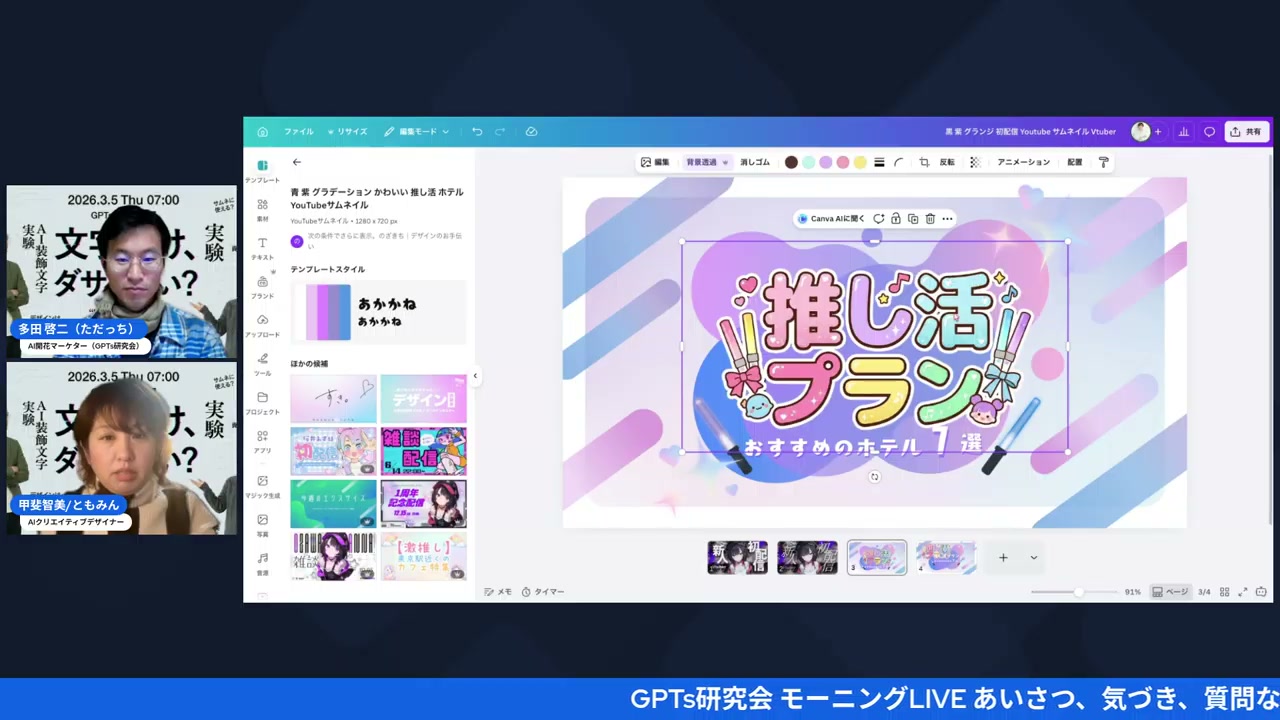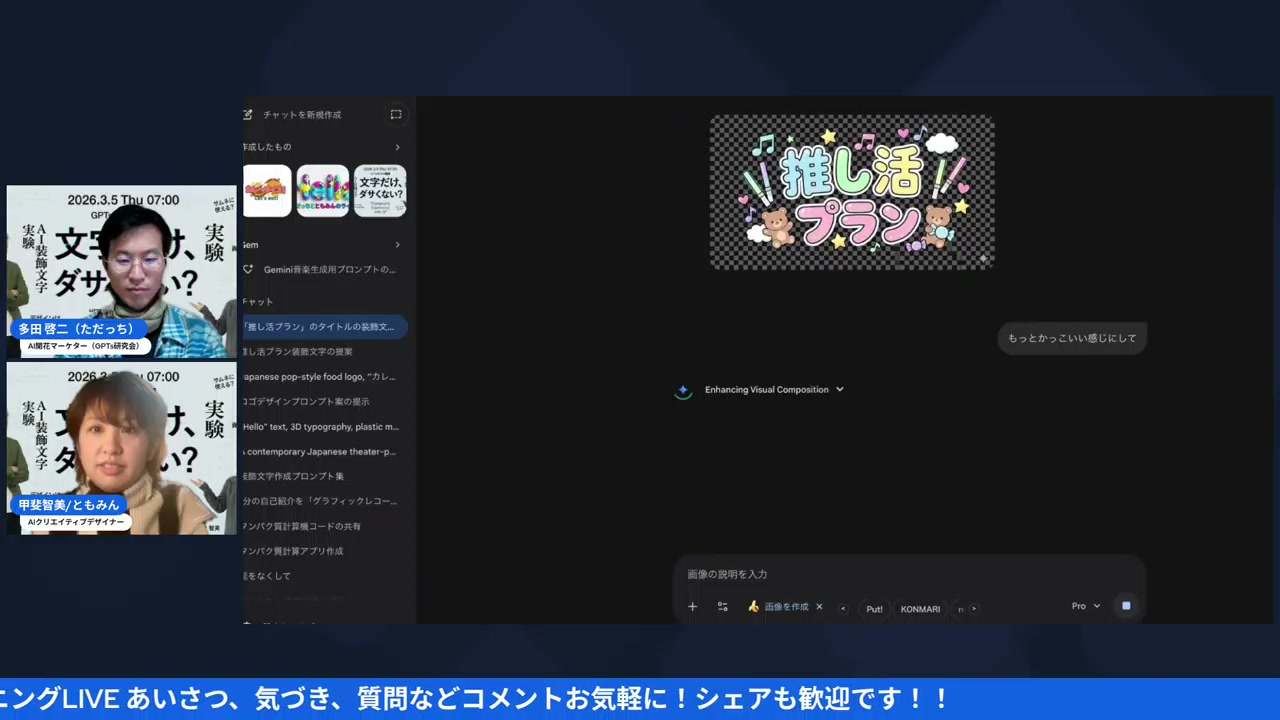
文字ひとつで印象が変わる、Canvaプロモード装飾文字実験
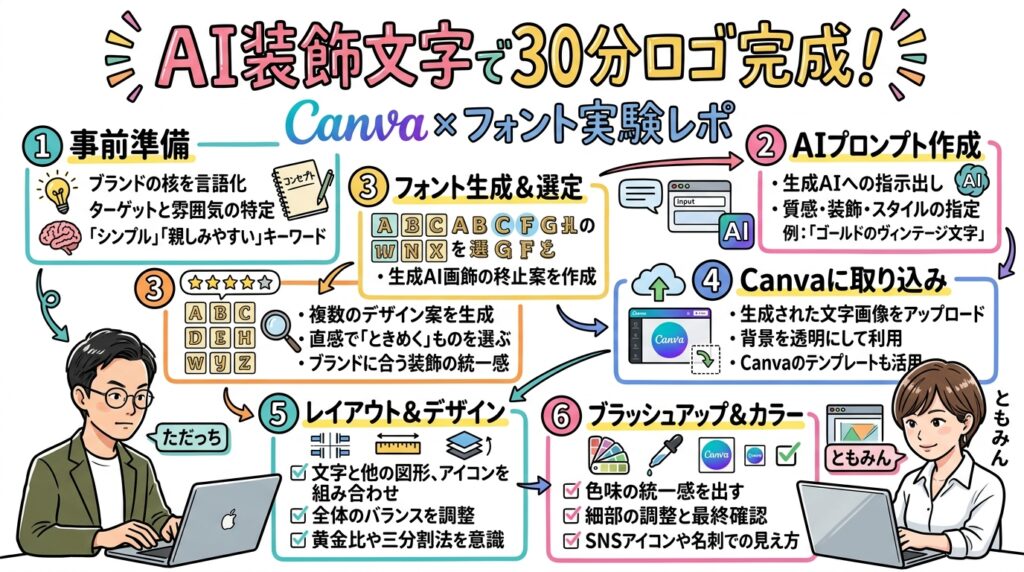
家事と子育てのスキマで経営する3方よしAI共創コンサルタントの田中啓之、ひろくん(@passion_tanaka)です。今回はともみん(甲斐智美)が語った、Canvaプロモードで文字を装飾するLIVEを紹介するね。木曜あさのGPTs研究会、進行役はただっち(多田啓二)。この日、私は登壇していなくて、画面の外から二人のやり取りをそのまま見ていた立場で、今日はお届けします。
いやー、この回は最初から最後まで「文字」の話しかしてないんだけど、それがめちゃくちゃ濃かった。テーマは「AI装飾実験」。ゴシックとミンチョ、たった2種類のフォントの見分け方から始まって、Canvaプロモードで装飾文字を生成し、背景を透過してレイヤーに重ねる。地味な操作の積み重ねが、最後には「同じ推し活プランのタイトルなのに、こんなに違うの?」というビフォーアフターにつながっていった。その一部始終を、今日は紹介するね。
文字ひとつで印象が変わる——AI装飾実験のはじまり
木曜あさのLIVEは、ただっちの挨拶から始まった。この日のテーマは「AI装飾実験」。文字ひとつで全然イメージが変わるし、そこにAIの力を借りられる時代になった、という導入だった。
ただっち(0:37〜)
「この文字にこのなんかえっと思いを込めるっていうのはすごいなというふうにいつも思っておりまして、今日はそんな文字装飾もAIの力も借りられるというところですね、実験してお届けしたいなと思っています」
文字に思いを込める、という言葉、私はすごく共感しました。
自己紹介を挟んで、ただっちは自身とともみんの出会いについても触れていた。友人と出会ったことで表現の幅が広がった、という話。
ただっち(0:37〜)
「友人とも出会ったことで表現の幅がすごく僕も広かったなと思っています。デザイン一つで思いを伝えられる可能性というのは広がっているんじゃないかなと思いますので、今日トモミンの文字装飾も楽しみにしておりました」
デザインひとつで思いを伝えられる、という視点、私はいいなと思いました。
正直、この時点ではまだ「文字の実験」がどれくらい面白いのか分からなかった。半信半疑。……でも、ともみんの一言で、それがちゃんと本気の実験だってわかる。
ともみん(1:41〜)
「私も最近ちょっと文字をAIで別に作るようになりまして、これをやるだけで結構パターンが変わってきたりビジュアルが大きく変わるなと思ったので、ちょっと今日はこの題にしたいなと思っております」
文字だけでビジュアルが大きく変わる、と私は感じました。この一言が、今日一日のテーマを決めていたんだなあと思う。
ただっちとともみんは、それぞれ「AI開花マーケター」「AIクリエイティブデザイナー」として自己紹介していて、二人とも普段からAIを使ったデザインの現場に立っている人たちだった。だからこそ、今日の実験は単なる思いつきじゃなくて、日々の仕事の延長線上にある本気の検証だったんだと思う。木曜のGPTs研究会は、こういう「実際にやってみせる」LIVEが多いんだけど、この回はその中でも特に手を動かす時間が長かった印象。二人のテンションも最初から高くて、コメント欄にも「おはよう」が続々と流れていた。
私、この冒頭のやり取りを見ながら、二人の関係性がすごくいいなと思っていた。ただっちがともみんを「今日トモミンの文字装飾も楽しみにしておりました」と紹介し、ともみんもそれに応えるように「私も最近ちょっと文字をAIで別に作るようになりまして」と自分の実感を重ねていく。この掛け合いのテンポの良さが、そのまま今日30分の中身の濃さにつながっていったんだと思う。文字装飾という一見地味なテーマを、ここまで前のめりに語れるのは、二人がAIとデザインの現場に日々向き合っている証拠なんだろうなあ。
あ、そうだ。ひとつ言い忘れてた。この日のテーマ名、正式には「AI装飾実験」なんだよね。実験。この言葉がすごく大事で……二人とも「これが正解です」って上から教える感じじゃなくて、「一緒にやってみましょう」っていう温度だった。私、そこがいちばん好きなんですよ。画面のこっち側で見ていても、失敗も含めて全部さらけ出してくれるから、こっちも身構えずに済む。
ぶっちゃけ、文字の話って地味でしょ。フォントがどうとか配置がどうとか、聞く前は「まあ知っといて損はないかな」くらいのテンションだった。……でもね。ともみんの『これをやるだけで結構パターンが変わってきたりビジュアルが大きく変わる』っていう一言で、一気に前のめりになっちゃった。たった文字ひとつで、作るものの印象が根っこから変わる。そんな話を、朝いちばんの30分でここまで掘り下げるLIVEって、なかなかないんですよ。だから今日のこのレポも、ぜひ最後まで付き合ってほしいなあと思ってます。
文字はまず2種類——ゴシックとミンチョの話
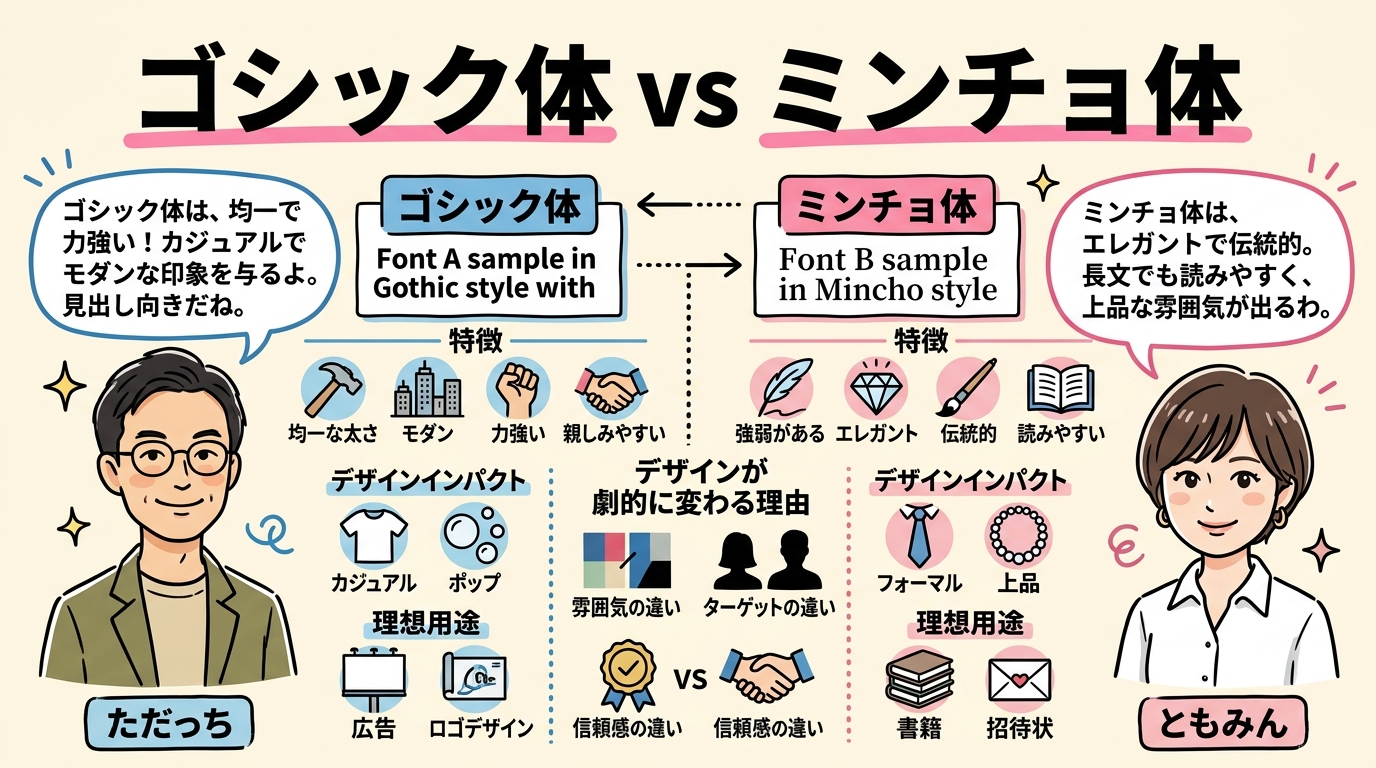
いくつかサンプルを見比べながら、ともみんが切り出したのは「文字は2種類だけ知っておけば十分」という話だった。デザイナーが見て「あ、この文字これだわ」ってわかるのも、結局この2種類の話に集約されるらしい。
ともみん(6:34〜)
「あれなんだよね。結構デザイナーの人がさ、こうやって見てて、あ、この文字これだわみたいなのって分かったりするんだけど。基本的に文字って2種類。2種類。日本語で言うと、」
でね、これが私には意外だったんですよね。フォントって選択肢が無限にあるように見えて、実は「尖ってるか、シュッとしてるか」の2軸に落とし込めるって話。シンプル。
この後、ともみんは「だいたいコシックかミンチョウの2種類」という表現でもう一度まとめ直していて、配置の話にもつながっていく。
ともみん(7:26〜)
「そうそうそうそう。だいたいコシックかミンチョウの2種類になっているので、これ多分でもねこういう感じだったらあとねよくあるのはこれ配置がねちょっといつもと違うとかいうときあると思うの」
フォントの種類だけじゃなく、配置までワンセットで印象が決まる——このことに私、この時点で気づかされました。
ただっちも「それね」と相槌を打ちながら聞いていて、二人の間ではもう当たり前の知識みたいだったけど、私にとっては新鮮な整理の仕方だった。ゴシックとミンチョ、この2択だけ覚えておけば、文字選びで迷う場面はぐっと減るんだろうなあ、と思いながら見ていた。派手なツールの機能紹介よりも、こういう地に足のついた話のほうが、実は一番使える知識だったりするんだよね。
面白いのは、この2種類の話が「機能の説明」じゃなくて「見た瞬間の印象の話」として語られていたところ。ゴシックは先っぽが尖っていて力強い印象、ミンチョはシュッとしていて上品な印象。デザインの専門用語を並べられるより、こっちのほうがずっと頭に残るなあと私は感じた。木曜LIVEでは毎回こういう、覚えやすい言い換えがぽんぽん出てくるのが特徴だなと、あらためて思う。
でね、私がこの「2種類だけ」って話を聞いて思ったのは……料理でいうと、包丁を全種類そろえる前に「切る」と「刻む」の2つを覚えるようなものだなあ、と。フォントも同じ。何百種類ある中から選ぶんじゃなくて、まず「ゴシックか、ミンチョか」。この2択にさえ落とせば、もう迷子にならない。入り口がこれくらい単純だと、はじめてでも手が動くんですよ。
しかもともみんは、フォントの種類だけじゃなくて『配置がちょっといつもと違うとかいうときあると思うの』って、置き方にまで話を広げてた。種類+配置。この2つがワンセットで印象を決めてるんだよね。……知ってしまえば当たり前。でも、言葉にしてもらえるまで、私はぼんやりとしか分かってなかった。ゴシックは力強い、ミンチョは上品——たったこれだけの物差しを手に入れるだけで、次に何か作るときの目線が変わる気がしたんですよ。
今回の題材である「推し活プラン」の文字も、結局はこの2種類のどちらに寄せるかで方向性が決まっていく。ゴシック寄りにすればしっかりした印象、ミンチョ寄りにすれば柔らかい印象。次のセクションで実際にともみんが手を動かしていく様子を見ると、この「2種類のどちらか」という判断がいかに最初の分かれ道になっているかがよくわかる。
文字の話って、つい難しく考えがちだけど、入り口はこれくらいシンプルでいいんだなと、私は今日の説明を聞いて肩の力が抜けた気がした。
「推し活プラン」の文字をCanvaプロモードでロゴにしてみる
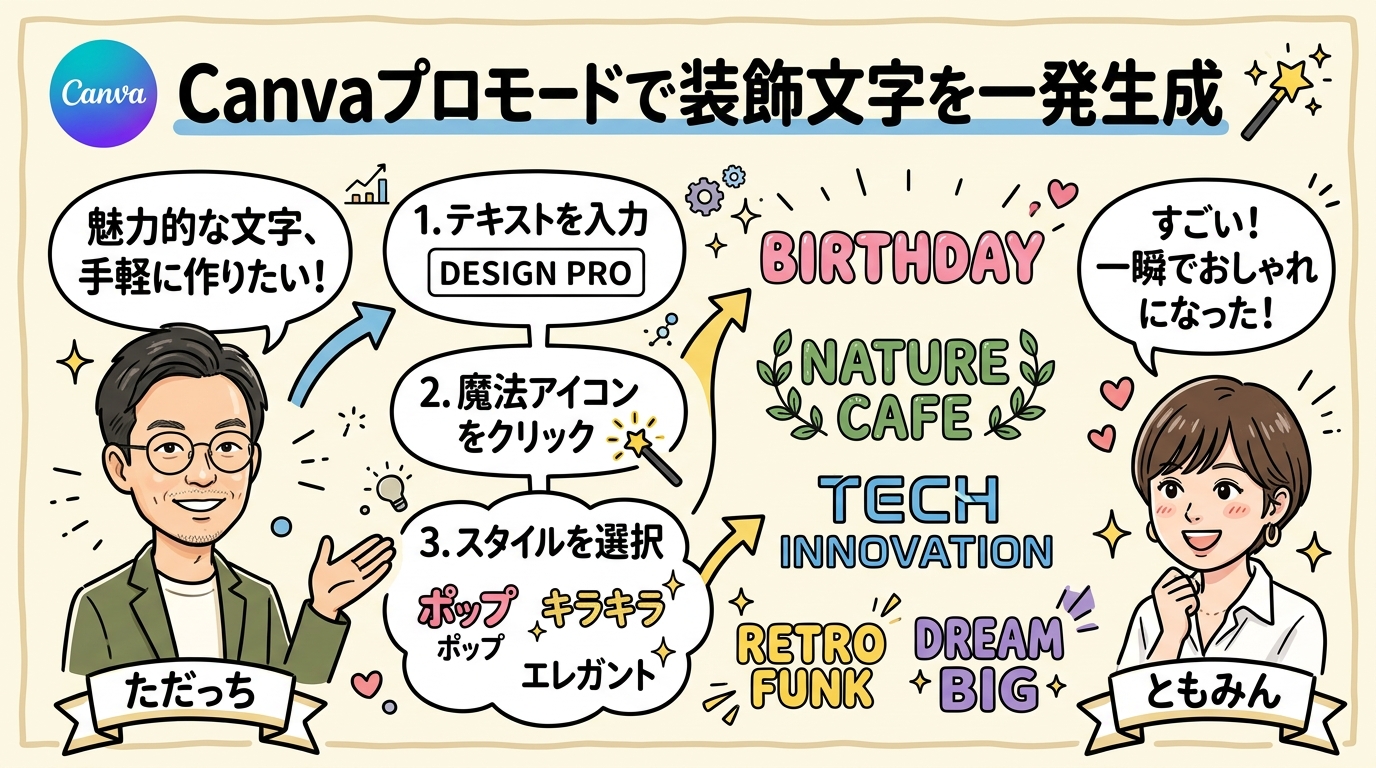
いよいよ実演パート。お題は「推し活プラン」というタイトル文字。画面上では「押し勝つプラン」って変換されたり、コメント欄で突っ込まれたりしながら、ともみんが実際にCanvaプロモードで装飾文字を生成していく。
ともみん(12:03〜)
「そっちかね。かつが、こっちが出てこない。おしかつプランってやつをちょっと1個作りたいと思います。おしかつプランの装飾文字を作っていきたいと思います。グリと。いくよー。どんなのが出るか知らないです。ちょっとここで調整もしていきたいなと思う」
「どんなのが出るか知らない」って言いながら生成ボタンを押す、あの瞬間の緊張感。私も画面越しにドキドキしてました。
でね、生成された装飾文字は、いったんポンチ画像として素材化して、そこからCanva上でレイヤー配置していくという流れだった。ともみんはこの手順を実況しながら進めていく。
ともみん(13:12〜)
「デザイナーならこう入れます、素材にしたいとこの感じで入れます。推し活プランのタイトル装飾ポンチ画像を作って素材に、プロモードでいきます。出るかなできるかな?動き出しました動き出しました。さっきは懐かしの絵文字みたいなやつが出てきた。あれなんだね、多分そういう2チャンネル系のああいう装飾系の出てくる」
懐かしの絵文字系が出てきちゃう、というAIあるあるも含めて、私は生々しくて面白かったです。
ちなみに、こういう装飾文字を背景ごと透過して使うには、Canvaの有料プランが必要という話も出ていた。ともみんは「有料プランがいいんだよ」とはっきり言い切っていて、無料でどこまでできるかを気にしていた私には、ちょっと現実を突きつけられた感じもあった。でも、それだけの価値がある仕上がりだったのも事実。文字数字だけの話じゃなくて、素材ひとつひとつに手間がかかっているんだなあと感じた場面だった。
実演を見ていて私が驚いたのは、生成→調整のスピード感だった。「どんなのが出るか知らない」と言いながらポチッと押して、出てきたものをその場で見て、良ければ採用、微妙なら作り直す。この判断のテンポが、画面のこっち側にいる私にもちゃんと伝わってきた。テレビの料理番組で完成品だけ見せられるより、こうやって試行錯誤の途中を全部さらしてもらうほうが、よっぽど参考になる。
あ、そうだ。ここで一個おもしろかったのが、画面で「推し活」が「押し勝つ」に変換されちゃって、コメント欄がざわついた場面。ライブ感、たっぷり。……でもね、ともみんはまったく動じないの。『どんなのが出るか知らない』って笑いながら、そのままグリッと生成ボタンを押していく。この「知らないけど押す」っていう姿勢、私はすごく学びになりました。完璧に指示を組み立ててから動くんじゃなくて、まず出す。出してから直す。デザインが苦手な人ほど、この順番なんだよね。